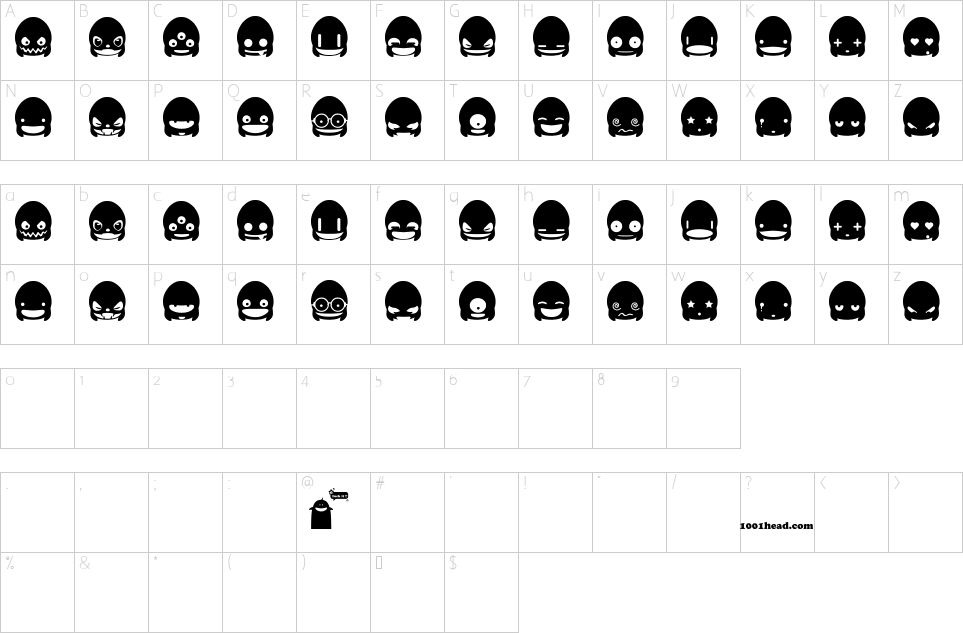
Aqui está uma breve descrição para a página de download da font ‘Ghost Punk Smileys’, adaptada ao tom solicitado: Através do site oficial, você pode baixar a popular e única ‘Ghost Punk Smileys Font’ sem custos. Esta font foi criada por Maelle Keita, uma designer talentosa cujo trabalho é sempre único e marcante. Ideal para aqueles que desejam adicionar um toque distinto a suas criações digitais, esta font tem sido baixada mais de 7300 vezes, demonstrando seu valor. Com sua paleta vibrante e estilo inovador, a ‘Ghost Punk Smileys Font’ é perfeita para quem busca dar um gás extra ao design de aplicativos ou sites. Seja você um designer web, desenvolvedor de software ou criativo de mídia social, esta font certamente encontrará seu lugar. Adicionar este único e divertido elemento a seus projetos pode torná-los mais memoráveis e inovadores, oferecendo uma maneira única de expressar-se no universo digital. Não perca tempo: é hora de incorporar o charme peculiar da ‘Ghost Punk Smileys Font’ em suas criações digitais.